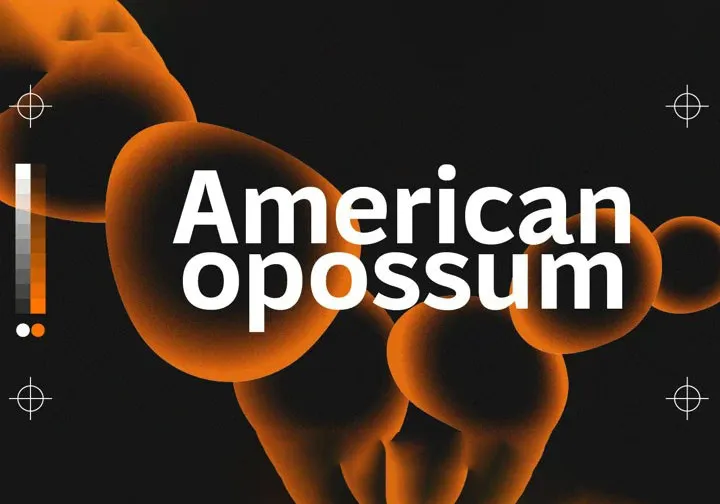
Prostir Sans Font
A Prostir Sans é uma nova adição à coleção de fuentes sem serif na 99designs que desliza pela categoria dos fonts sans serif. Inspirada nas anúncios alegres e coloridos das panfletas e revistas do início da década de 1990, essa fonte apresenta grandes alturas x-height e pequenos trapinhos de tinta, oferecendo um tom emocionante que parece livre, com curvas leves e conexões contrastantes. Como uma fonte sem serif, ela oferece uma aparência clean e moderna para qualquer projeto visual, seja ele em aplicações digitais ou impressas. A Prostir Sans é perfeita para criar textos chamativos e agradáveis aos olhos, adequada tanto para design editorial quanto para criação de logotipos que desafiam as normas tradicionais do tipo sem serif.